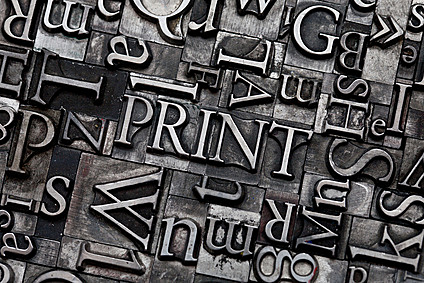
caratteri suddivisi in: VENEZIANI o UMANISTI e GARALDE o ROMANI ANTICHI
Bibbia a 42 linee (B 42); perché stampata su 42 linee di testo.
usato font Blackletter -
Johan Gutenberg costruisce la prima macchina per la stampa dei caratteri mobili
Primo carattere tipografico con caratteri Romani, inventato da Nicolas Jenson (Francese)
Aldo Manunzio famoso per aver diffuso molti libri economici perche stampati in italic, infatti il corsivo occupa meno spazio e permette di inserire più lettere su una pagina
Il romano del Re
John Basketville, transizionale per eccellenza
con la rivoluzione industriale nascita del design iniziarono creare dei font per i manifesti. Avevano lo scopo di attirare l'attenzione
Romani moderni
Bodoni (1798) e Didot (1784-1811) -
sviluppato da progettisti Tedeschi per la fonderia Berthold
con esponenti come William Morris e John Ruskin
Edward Johnston pubblica un manuale per una buona progettazione tipografica
Johnston Sans
(metropolitana di londra) -
Eric Grill collaboratore di Jhonston
Univers (1952-1960)